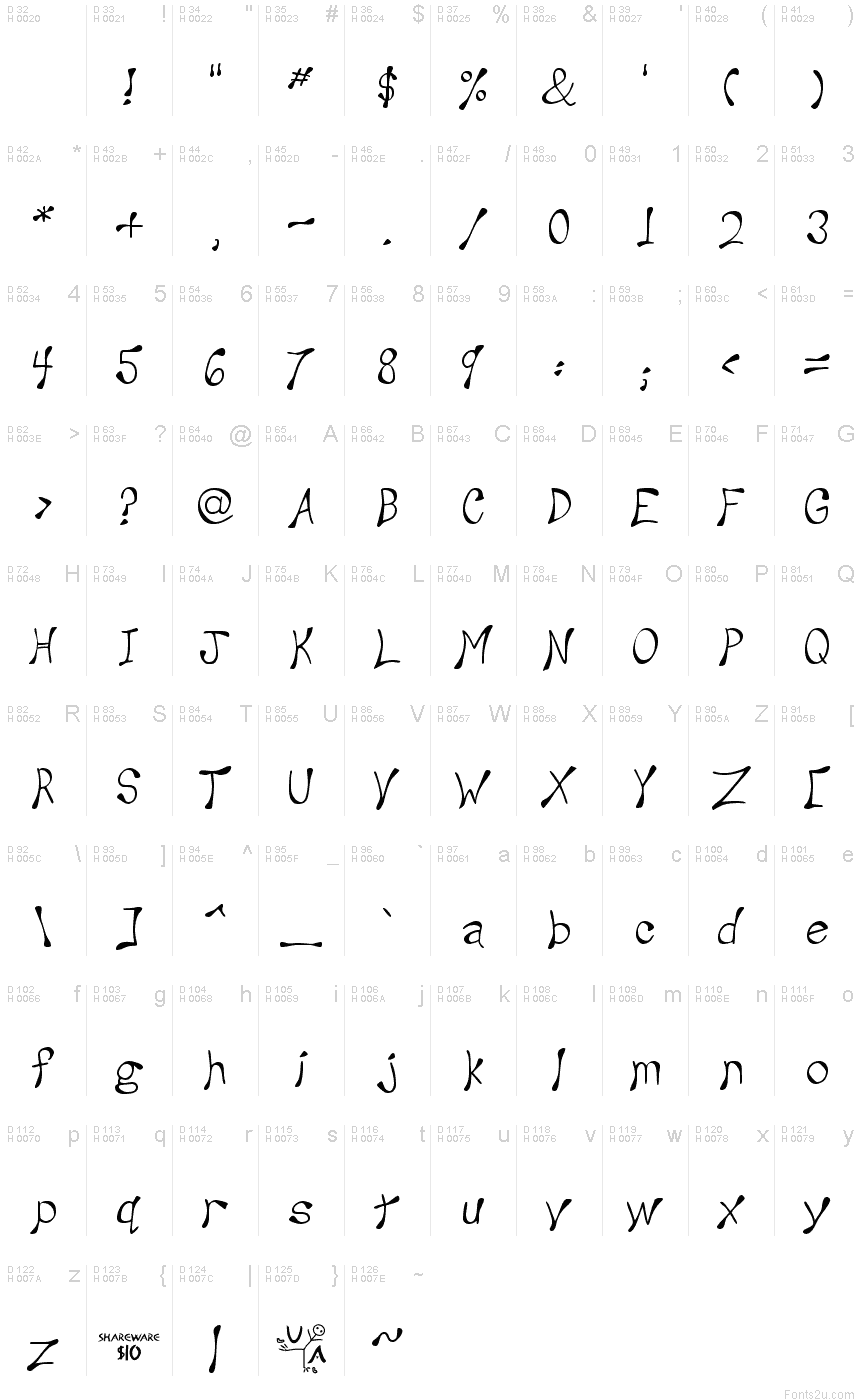
Wesley من UnAuthorized Type هو خط عرض مجاني بنمط الكوميكس، يتميز بلمسة يدوية عفوية. تتبع الحروف إيقاعاً مرحاً يشبه القصص الخيالية، حيث تمزج بين الضربات العالية، والحلقات المستديرة، والزوايا الناعمة، مما يمنحه طابعاً غير متكلفٍ يبتعد عن المثالية المبالغ فيها، تماماً مثل خطوط الـ novelty الشائعة في أواخر التسعينيات.
يعمل هذا الخط بشكل رائع في أغلفة كتب الأطفال، وعناوين المجلات المستقلة (Zines)، وبطاقات المعايدة، وملصقات المدارس، وقوائم الطعام المبتكرة في المقاهي، حيث يمكن لخط مجاني أن يضفي صوتاً ودوداً ويدوي الصنع. بفضل أشكاله الحيوية وغير المنتظمة قليلاً، يعد Wesley مناسباً بشكل خاص للعناوين القصيرة، والبطاقات التعريفية، والشعارات التي تبحث عن الدفء دون أن تصبح ذات طابع طفولي مفرط.